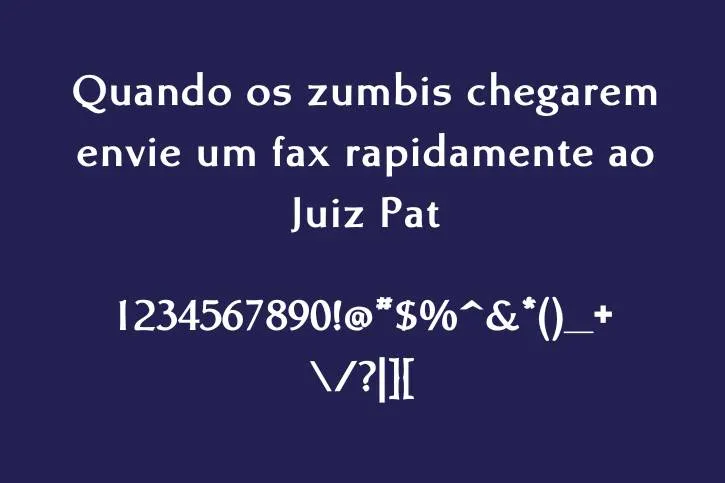
A fonte Biblia é uma família de fontes sem serifa. Esta fonte tem seis estilos, desenhados por Carl Albert Fahrenwaldt em 1929 e publicados pela Hackberry Font Foundry. Seu design é elegante e sóbrio, com linhas limpas e uma estética clássica que evoca um senso de seriedade e reverência, adequado para textos sagrados e materiais relacionados à religião.
É ótimo para fazer uma combinação forte com a Fonte Larke Sans, que é uma fonte semelhante. Uma característica marcante é a excelente legibilidade, mesmo em tamanhos pequenos. Isso o torna ideal para uso em textos longos, onde clareza e facilidade de leitura são essenciais.
A fonte também vem em uma variedade de pesos e estilos, tornando-a versátil e adaptável a diferentes contextos de design. Pode ser usado para criar uma hierarquia visual sem comprometer a consistência estética. Além disso, foi projetado com atenção aos detalhes, incluindo caracteres especiais e ligaduras que contribuem para sua aparência refinada e artesanal.
Família de Fontes Biblia
- Biblia Regular
- Biblia Bold
- Biblia Semi Bold
Por Que a Fonte Biblia é Tão Popular?
É popular por diversos motivos, principalmente devido à sua estética clássica e elegante. Essa familiaridade visual evoca um senso de tradição e seriedade. É apreciado pela atenção aos detalhes, incluindo caracteres especiais e ligaduras que acrescentam um toque sofisticado e artesanal ao design tipográfico.
Essa fonte também é boa para fazer uma combinação forte com a fonte Doom. Além disso, foi projetado com foco na legibilidade, mesmo em tamanhos pequenos ou em condições de baixa resolução. A variedade de pesos e estilos disponíveis também contribui para sua popularidade, permitindo aos designers criar uma hierarquia visual.
Melhores Usos da Fonte Biblia
- Títulos e cabeçalhos em materiais impressos, como pôsteres e folhetos.
- Design de logotipos e marcas comerciais para empresas e marcas que buscam uma estética moderna e elegante.
- Combine-a com a Helldorado para criar mídia digital, como banners, postagens em mídias sociais e infográficos.
- Criação de materiais promocionais, como cartões de visita e catálogos, para transmitir uma imagem sofisticada.
- Embalagens de produtos, proporcionando uma aparência atraente e contemporânea nas etiquetas e caixas.
- Utilização em projetos de branding, com a tipografia sendo incorporada à identidade visual da empresa.
- Criação de materiais de sinalização, como banners e placas, para comunicação visual eficaz e atrativa.
Vista da Fonte Biblia
Qual é o estilo da fonte Biblia?
É uma família de fontes sem serifa. Esta fonte possui seis estilos, desenhados por Carl Albert Fahrenwaldt em 1929 e publicados pela Hackberry Font Foundry
Qual é a melhor característica da fonte Biblia?
Seu design é elegante e sóbrio, com linhas limpas e uma estética clássica que evoca um senso de seriedade e reverência.